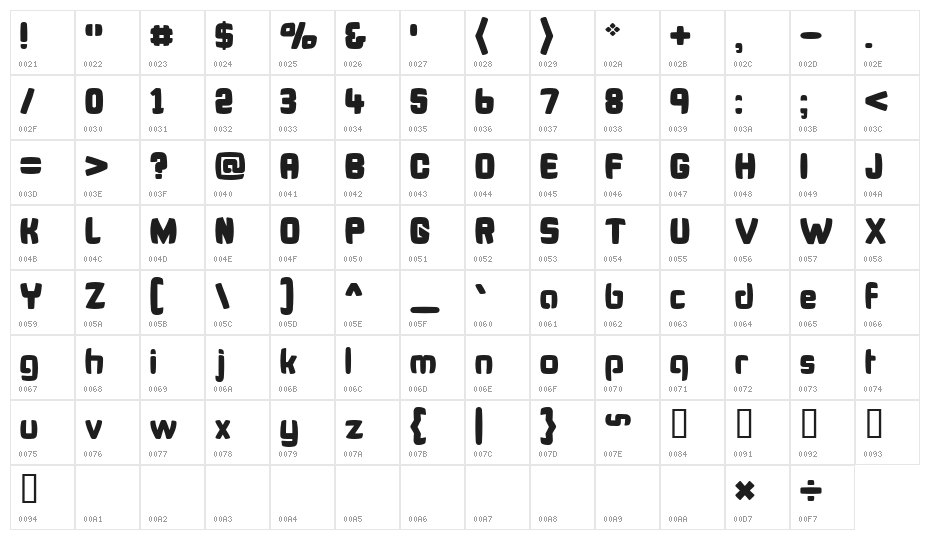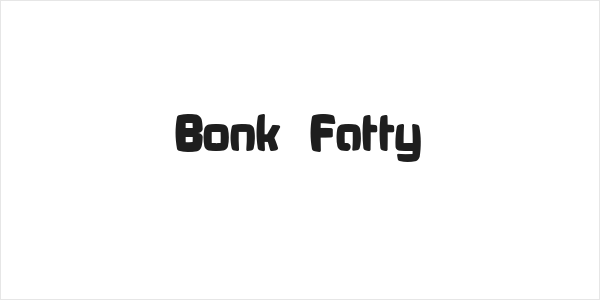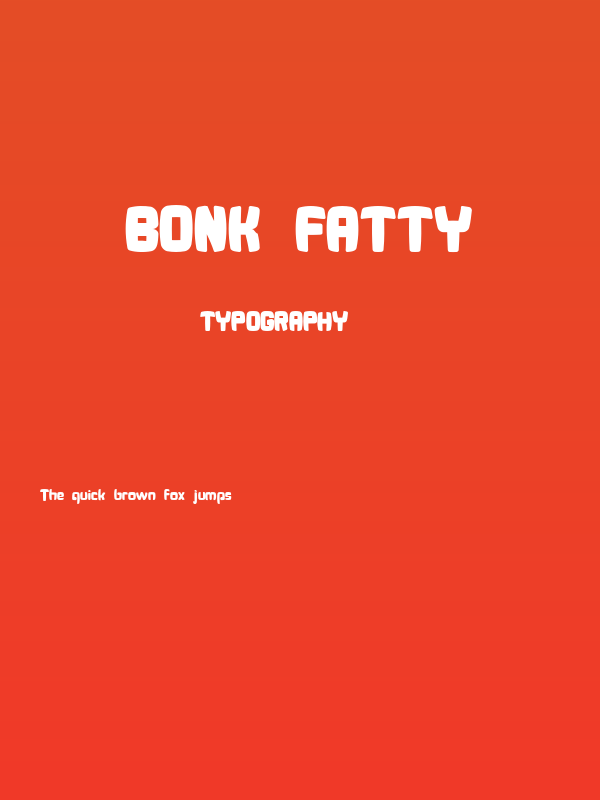
Bonk Fatty Font
| Gesamtstil | Playful |
| Vorgeschlagene Projekte | Perfect for children's books, playful branding, posters, and social media graphics. |